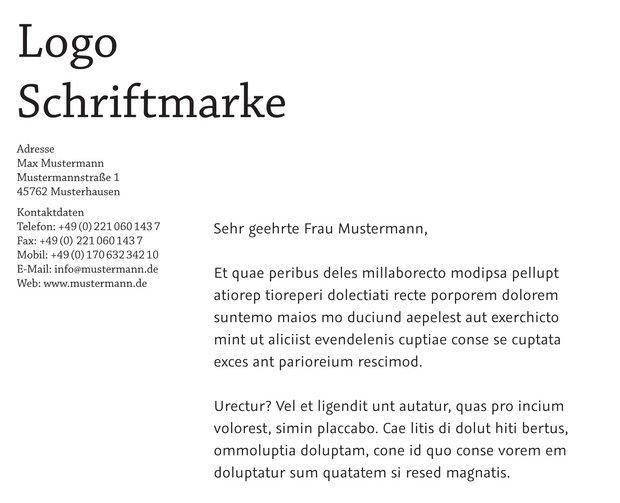
Chaparral Pro sucht harmonische Schrift für Brieftext
ich suche passende Schrift für Text eines Geschäftspapiers.
Die dynamische, serifenbetonte Linear Antiqua Chapparal würde ich gern für Absenderdaten verwenden.
Diese kommt bereits im Logo vor und sollte in der Hinsicht erhalten bleiben.
Ich persönlich fände die Graublau Sans von Georg Seifert als humanistische Grotesk sehr ansprechend,
frage mich aber, ob es so gut ist eine Grotesk mit einer serifenbetonten Antiqua zu mischen.
Wie steht ihr dazu?
Oder würdet ihr mir eine andere Kombination mit Chaparral empfehlen?
beide schriften regular. chaparral in 8pt / graublau in 11pt